Meski jadul, kepopuleran mesin ketik (typewriter) masih bertahan hingga sekarang. Alasannya mungkin sederhana, kesan klasik dan nostalgia yang ditimbulkannya sulit untuk ditolak. Font typewriter ini memberikan sentuhan vintage dan autentik pada desain, yang membuatnya tetap diminati oleh banyak orang.
Penggunaannya pun bervariasi, mulai dari proyek desain grafis hingga dokumen formal. Font typewriter juga sering digunakan dalam membuat poster, logo, dan bahkan desain t-shirt. Oleh karena itu, font ini masih menjadi pilihan yang populer bagi banyak desainer dan pengguna font. Nah, apabila Anda sedang mencari font mesin ketik gratis, dalam artikel ini, kami telah merangkum 35 macam font mesin ketik (typewriter) klasik dan gratis yang bisa langsung Anda download. Yuk, lihat daftarnya di bawah ini!
Font pertama adalah Typewriter. Font ini menampilkan gaya klasik mesin ketik dengan karakteristik seperti ketebalan dan jarak antar karakter yang khas. Cocok digunakan untuk memberikan nuansa vintage pada desain grafis atau dokumen formal.
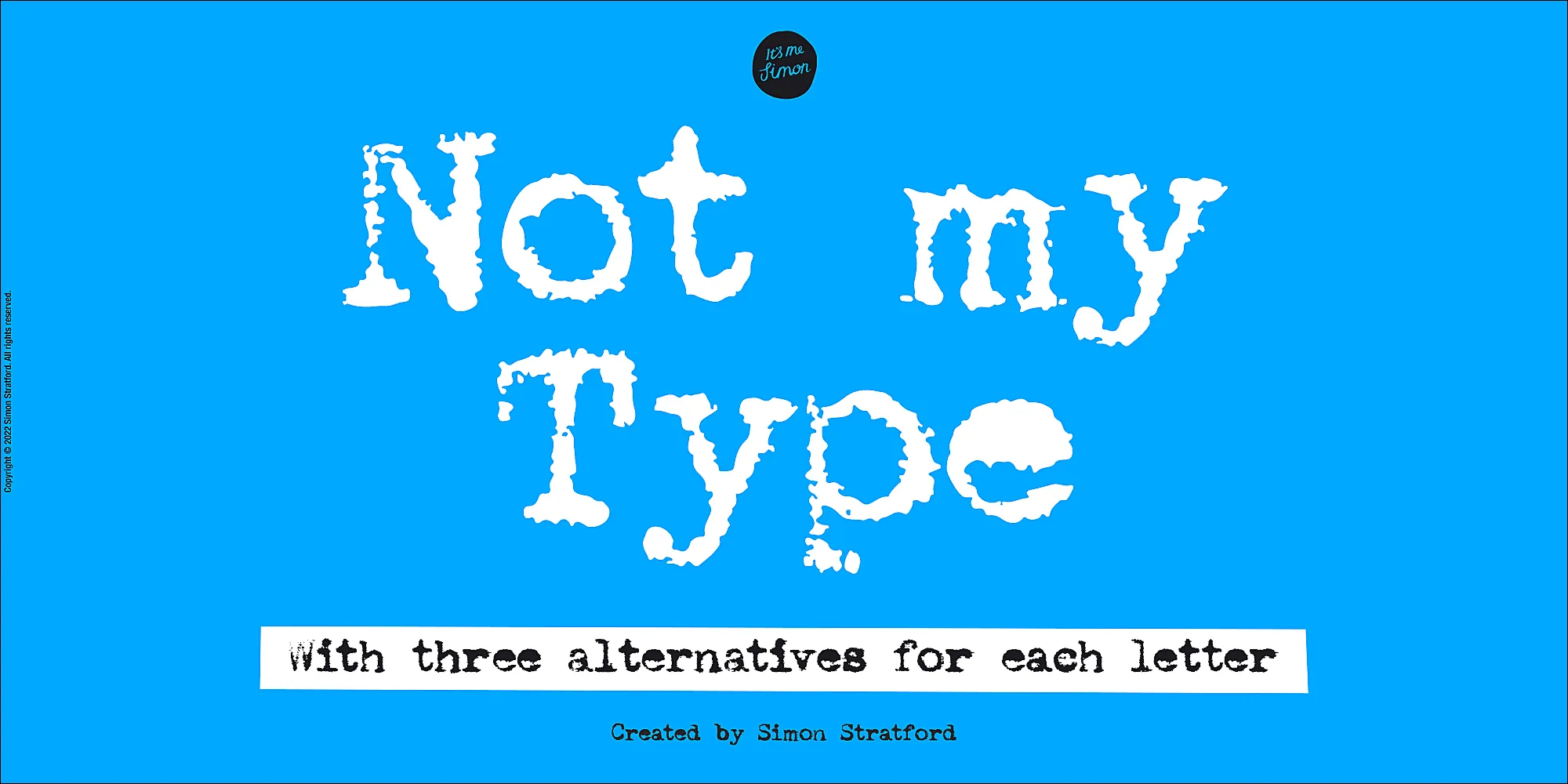
Font kedua adalah Not My Type, mengusung nuansa yang sedikit berbeda dengan tambahan sentuhan modern, font ini cocok untuk desain-desain yang ingin terlihat klasik namun tetap segar dan berbeda.
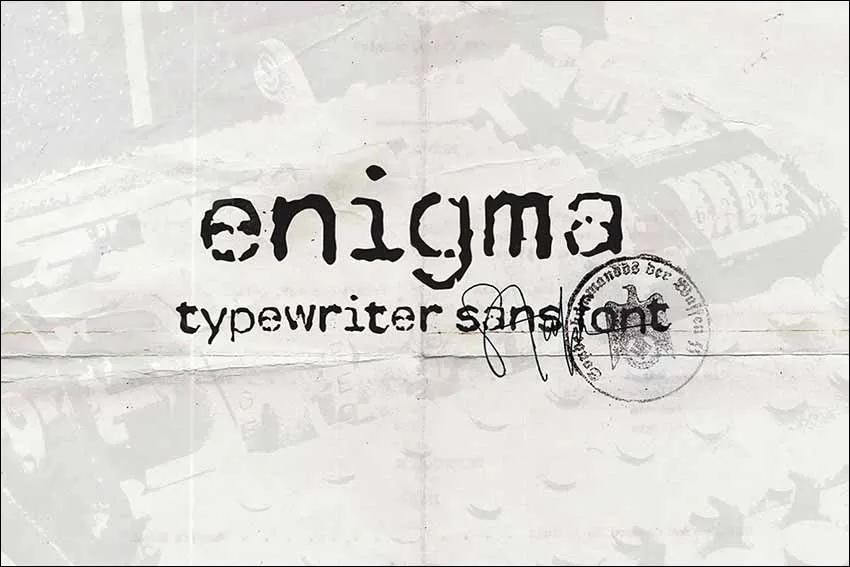
Selanjutnya adalah font Enigma. Font ini memiliki ciri khas huruf-huruf yang agak berdesakan dan tidak rapi, meniru gaya mesin ketik klasik yang mungkin telah mengalami keausan. Cocok untuk memberikan sentuhan unik pada desain-desain retro.
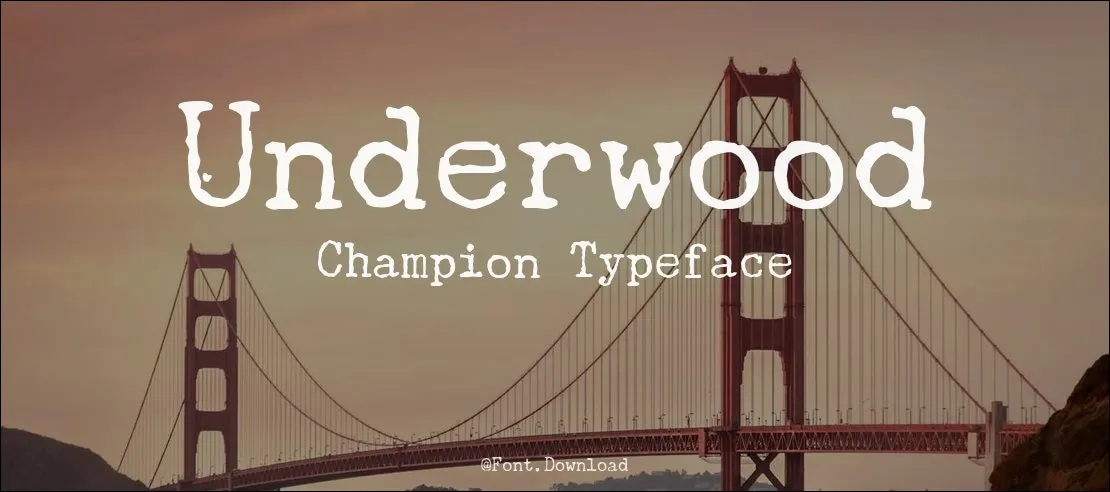
Underwood Champion merupakan font yang mengingatkan pada mesin ketik Underwood klasik. Huruf-hurufnya memiliki bentuk yang kokoh, jelas dan mudah dibaca. Cocok untuk dokumen formal dan desain logo yang membutuhkan kesan klasik.
Old English Std memiliki gaya yang mengingatkan pada huruf-huruf zaman dulu, cocok digunakan untuk desain-desain yang menginginkan tampilan yang megah dan klasik, seperti undangan atau logo.
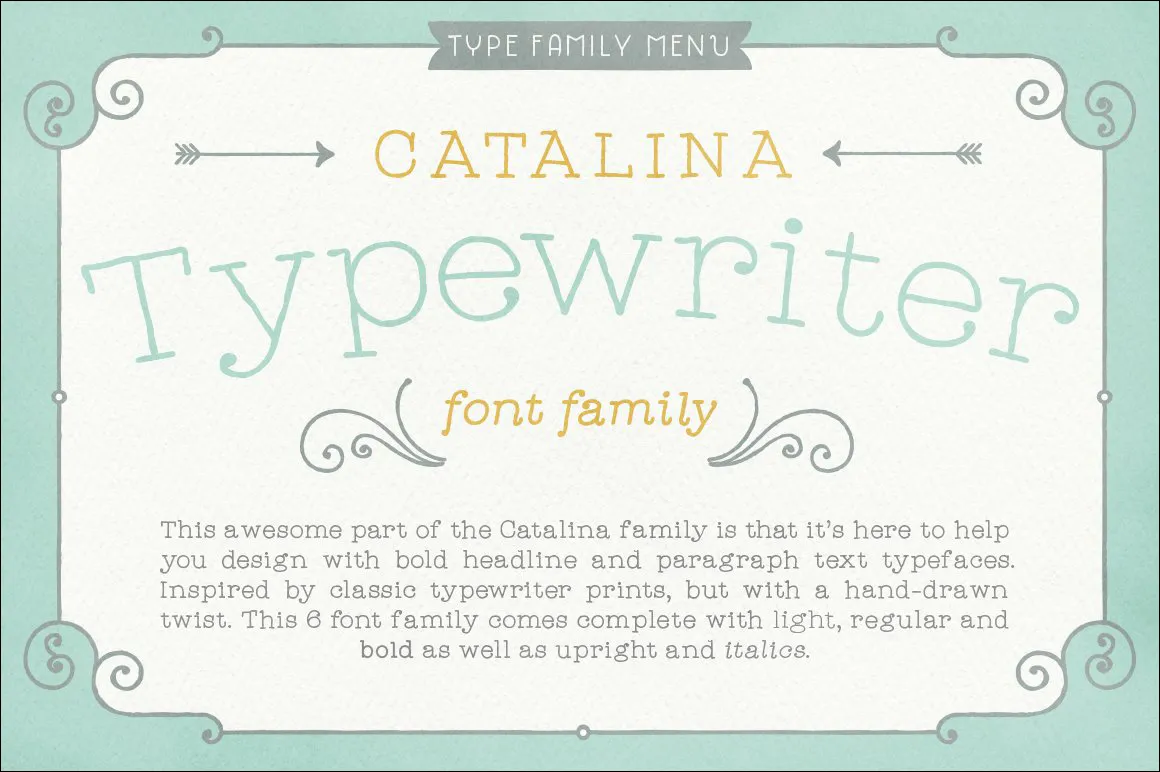
Catalina menampilkan karakteristik mesin ketik klasik dengan sentuhan modern yang ringan, cocok untuk berbagai proyek desain yang membutuhkan kombinasi antara nostalgia dan kekinian.
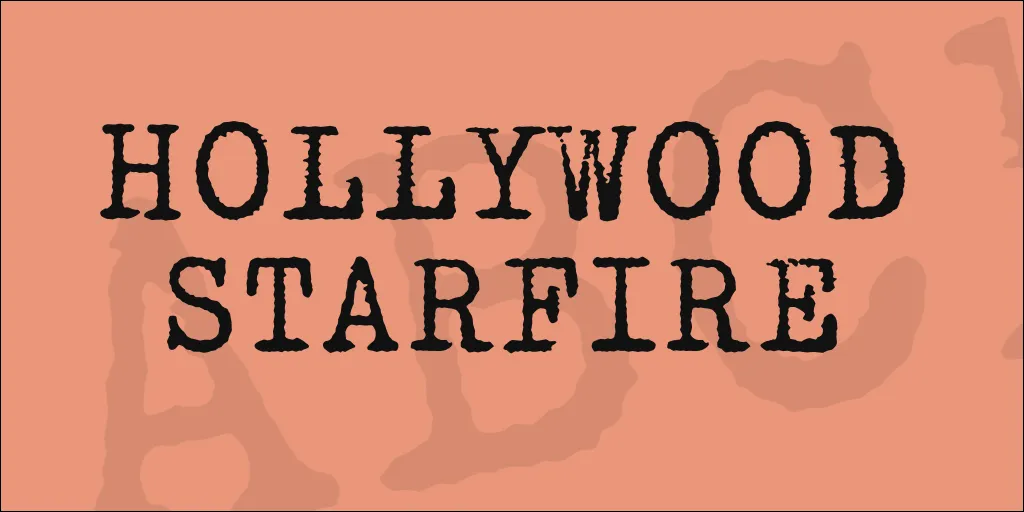
Font ini memiliki gaya yang elegan dan klasik modern, cocok digunakan untuk desain t-shirt atau poster yang ingin menciptakan kesan glamor dan eksklusif seperti di dunia hiburan Hollywood.
Appareo Black memiliki karakteristik tebal dan kuat dengan sentuhan vintage yang kuat, cocok untuk desain-desain yang membutuhkan tampilan yang mencolok dan berani.
Font ini menggabungkan antara klasik dan modern dengan sempurna, cocok untuk berbagai proyek desain yang membutuhkan tampilan yang bersih dan profesional.
Font ini menampilkan gaya yang ringan dan mudah dibaca, cocok untuk berbagai jenis desain baik yang formal maupun non-formal.
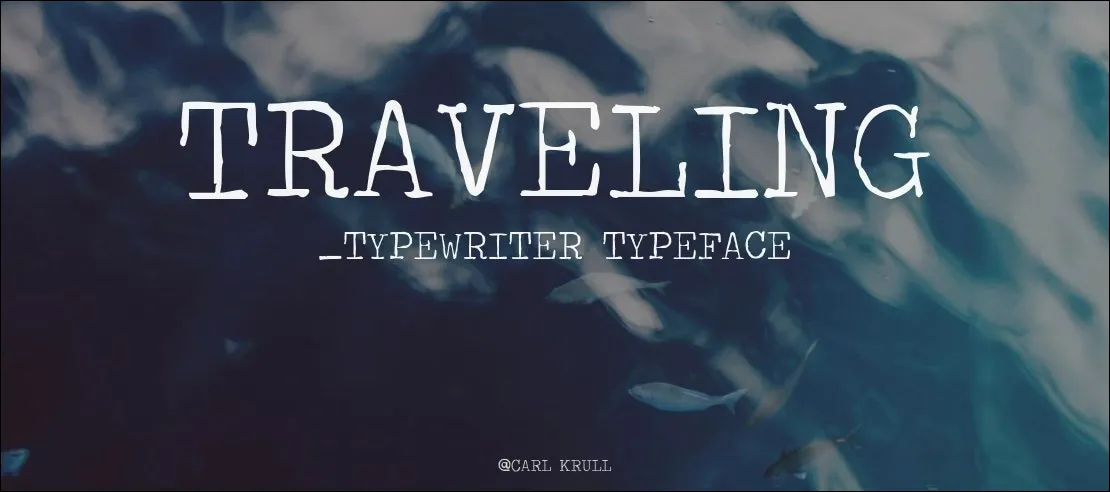
Traveling Typewriter secara khusus meniru tampilan huruf dari mesin ketik klasik, cocok untuk proyek-proyek desain yang ingin menampilkan nuansa nostalgia.
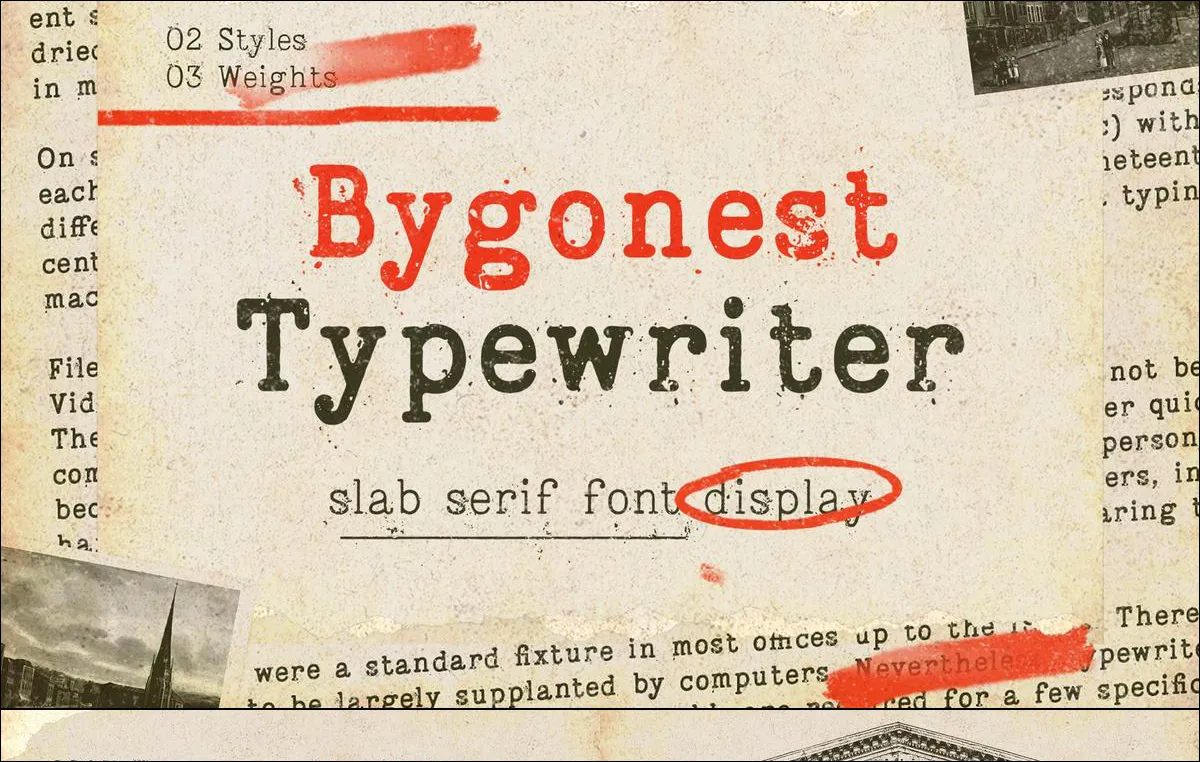
Bygonest Old menghadirkan tampilan klasik dengan kelembutan yang menyenangkan, cocok digunakan untuk berbagai proyek desain yang membutuhkan sentuhan nostalgia.
BD Westside memiliki ciri khas yang lega dan berkelas, cocok untuk berbagai proyek desain yang menginginkan tampilan yang elegan dan klasik.
ITC Benguiat Std menghadirkan tampilan yang megah dan berkelas dengan sentuhan klasik yang kuat, cocok untuk berbagai jenis proyek desain yang menginginkan kesan yang megah.
Font ini menampilkan gaya huruf yang kaku dan kuat, cocok untuk desain-desain yang membutuhkan tampilan yang serius dan profesional.
Silk Remington Pro menampilkan tampilan yang ringan dan halus, cocok untuk berbagai proyek desain yang membutuhkan tampilan yang elegan dan berkelas.
Font ini menampilkan karakteristik mesin ketik klasik dengan sentuhan bohemian yang unik, cocok untuk proyek-proyek desain yang ingin terlihat kreatif dan berbeda.
Special Elite memiliki tampilan yang kuat dan berani dengan sentuhan vintage yang khas, cocok untuk desain-desain yang ingin menampilkan kesan yang berbeda dan unik.
Adler dikenal dengan tampilan yang elegan dan berkelas, cocok untuk berbagai proyek desain yang membutuhkan tampilan yang mewah dan anggun.
Ghostwriter cocok digunakan untuk desain-desain yang ingin menampilkan nuansa retro dengan sentuhan misterius dan menarik.
Beberapa faktor yang perlu diperhatikan dalam penggunaan font mesin ketik jadul antara lain ukuran huruf yang sesuai, kontras yang mencukupi, serta konsistensi dalam penggunaan font di seluruh desain.